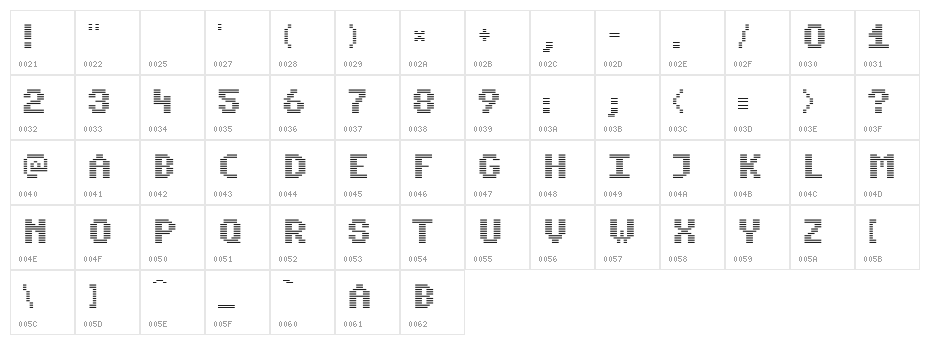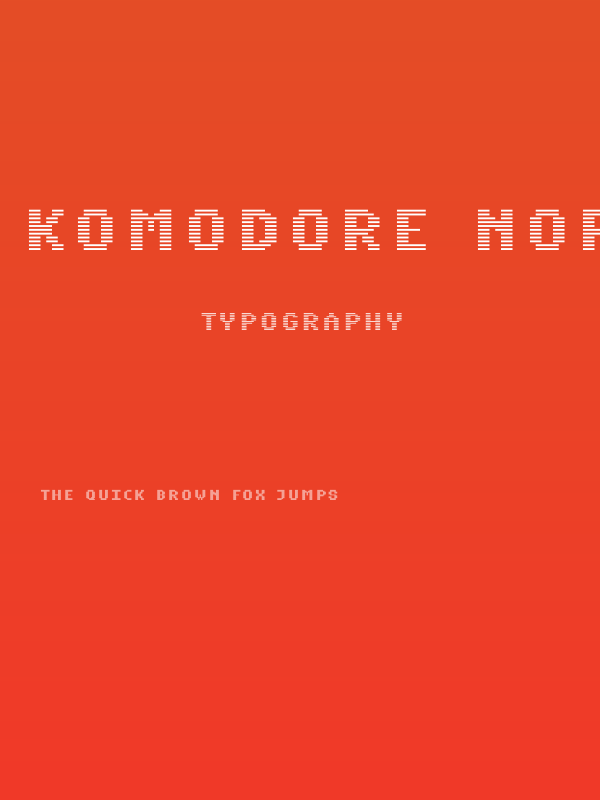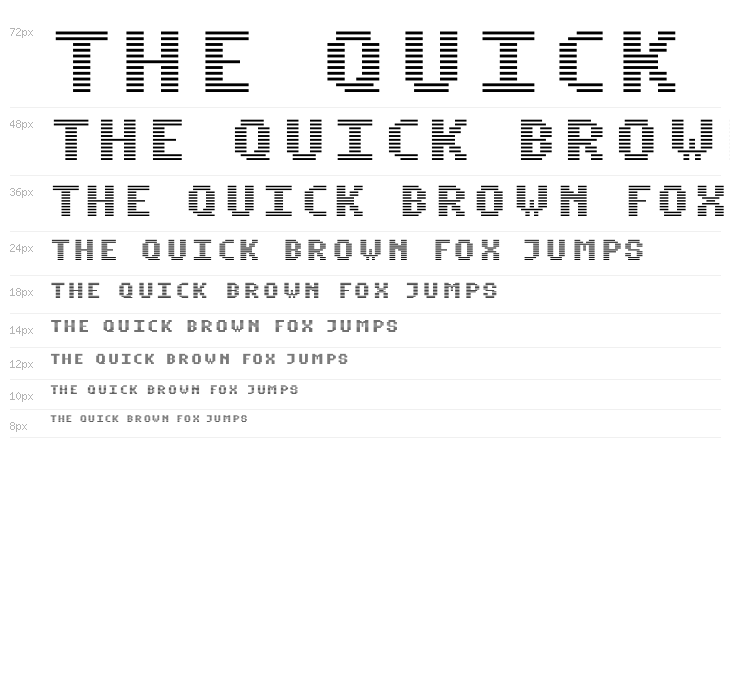
Komodore Normal Font
| Progetti proposti | Ideal for tech-related branding, digital art projects, video game interfaces, and modern poster designs. |
Komodore Normal